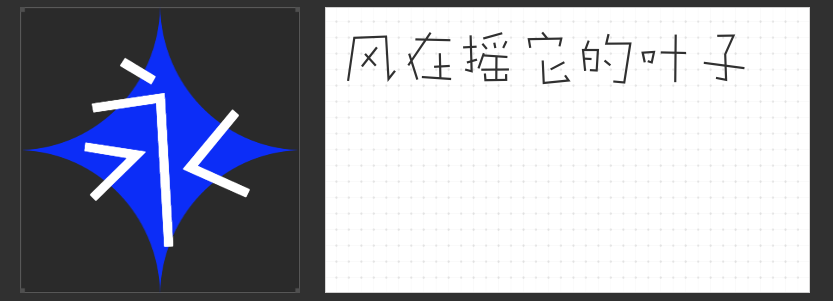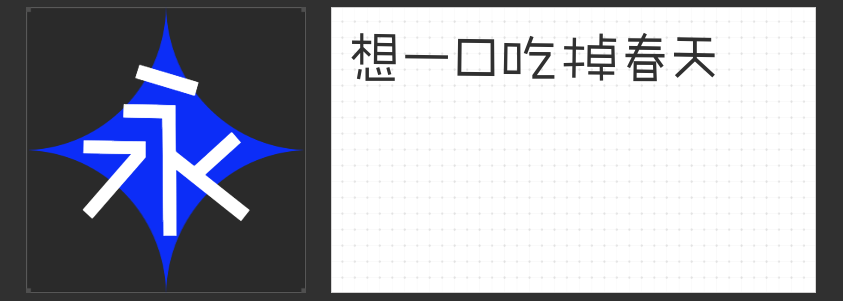
💕卡通字体大推荐:让你的设计作品充满童趣与活力💕
在设计作品中,字体选择至关重要。一款合适的字体能够瞬间提升作品的视觉效果,传达出特定的情感和氛围。今天,我要为大家推荐四款充满童趣与活力的卡通字体。
首先,让我们来看看“字恋狂风摇简 常规”。这款字体仿佛带着温暖的气息,笔画摇摇晃晃,歪歪扭扭,给人一种手写的感觉。字体比例故意做出失衡夸张的样子,仿佛被风吹过,让人感受到一种轻松愉悦的氛围。正如那句“草在结它的种子,风在摇它的叶子。我们站着,不说话,就十分美好。”,这款字体能够完美诠释这种宁静而美好的情感。
接下来是“励字敲可爱简 常规”。这款字体略带俏皮,充满趣味与想象。手写的圆润线条在保留辨识度的前提下,省略了部分笔画,使得字体更加简单明快。独特的形式和用心书写的随性,让这款字体更具手绘感,带来手写的柔软和温暖。无论是用于海报设计还是广告制作,都能让你的作品充满趣味和吸引力。
再来看看“字恋狂漫野 絮风”。这款字体以手写感为基础,结构张弛有度,布白空间通透。不同字型有细微大小变化,大小错落,富有节奏感,使版面更加活跃。笔画设计简洁而不呆板,去钩处理和“断开”特点的运用,使得字体更加灵动有趣。这款字体适合用于各种创意设计和广告宣传,能够瞬间吸引人们的目光。
最后是“字恋狂丸粒简”。这款字体的字型可爱,笔画两端和转折的地方都加上了圆角处理,使其圆润可爱。笔画圆头圆尾,富有独特的亲和力。无论是用于儿童教育材料还是卡通形象设计,这款字体都能让你的作品更加生动有趣,深受孩子们的喜爱。
总之,这四款卡通字体各具特色,都能为你的设计作品增添一份童趣与活力。不妨试试它们,让你的作品更加出彩吧!